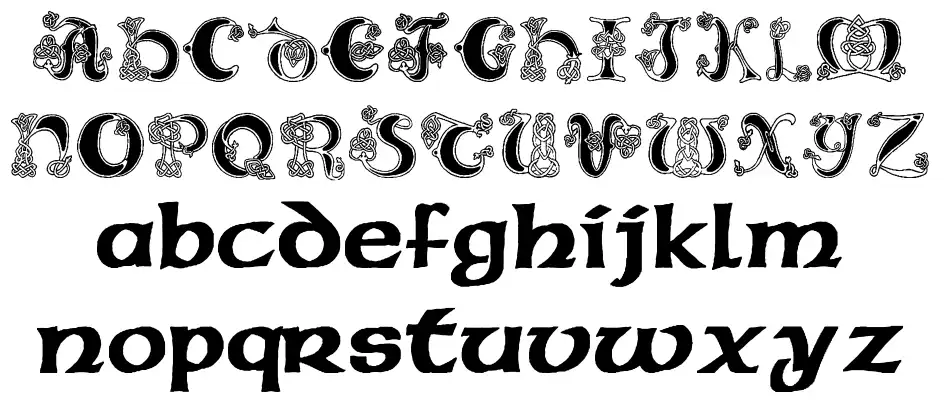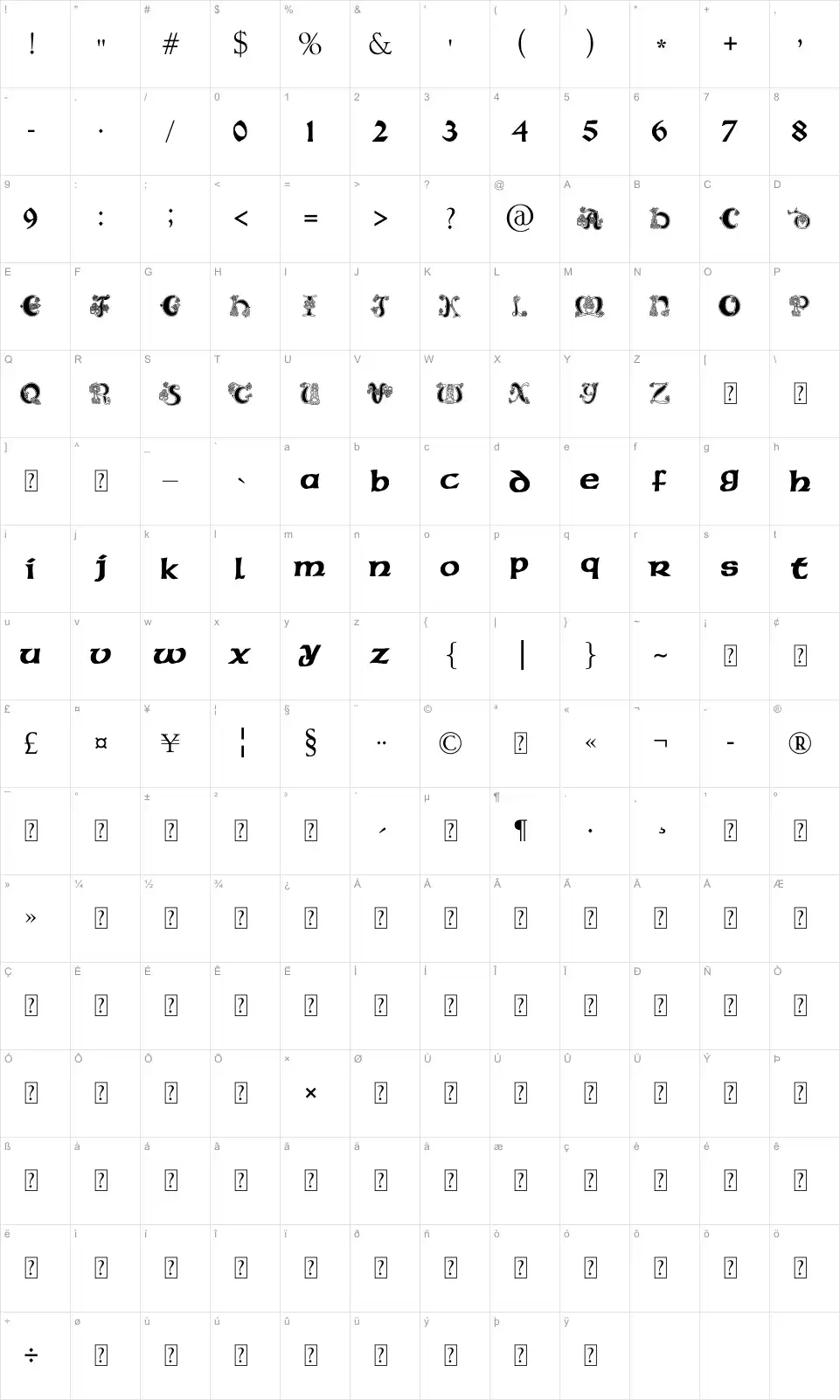
A Pauls Celtic Font 2 é uma fonte gothic de estilo celta, criada pelo designer Paul. Se você está procurando esta fonte, agora é a hora de descobrir como ela se destaca em seu design. Seja para uso pessoal ou profissional, você pode baixar a fonte diretamente ou gerar um visual de texto personalizado online para ver como ela se assemelha antes de utilizá-la. Esta fonte, que se destaca na categoria Gothic > Celtic, foi adicionada em 12 de julho de 2022 e já foi baixada milhares de vezes, com um total de 2148 downloads. Com um tamanho de 99 KB, é compacta e fácil de usar. Para mais informações, visite o site do designer, http://ViciousInk.net. Esta fonte é licenciada sob a forma de software de doação, o que torna ainda mais conveniente e acessível para seus usuários.
Categoria: Gothic › Celtic
Designer: Paul